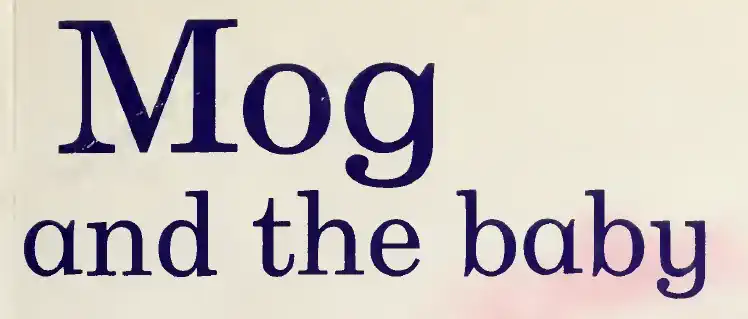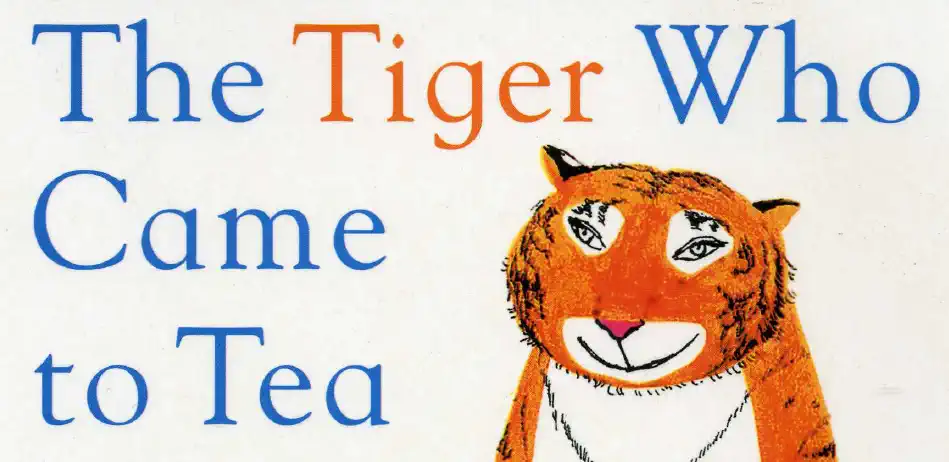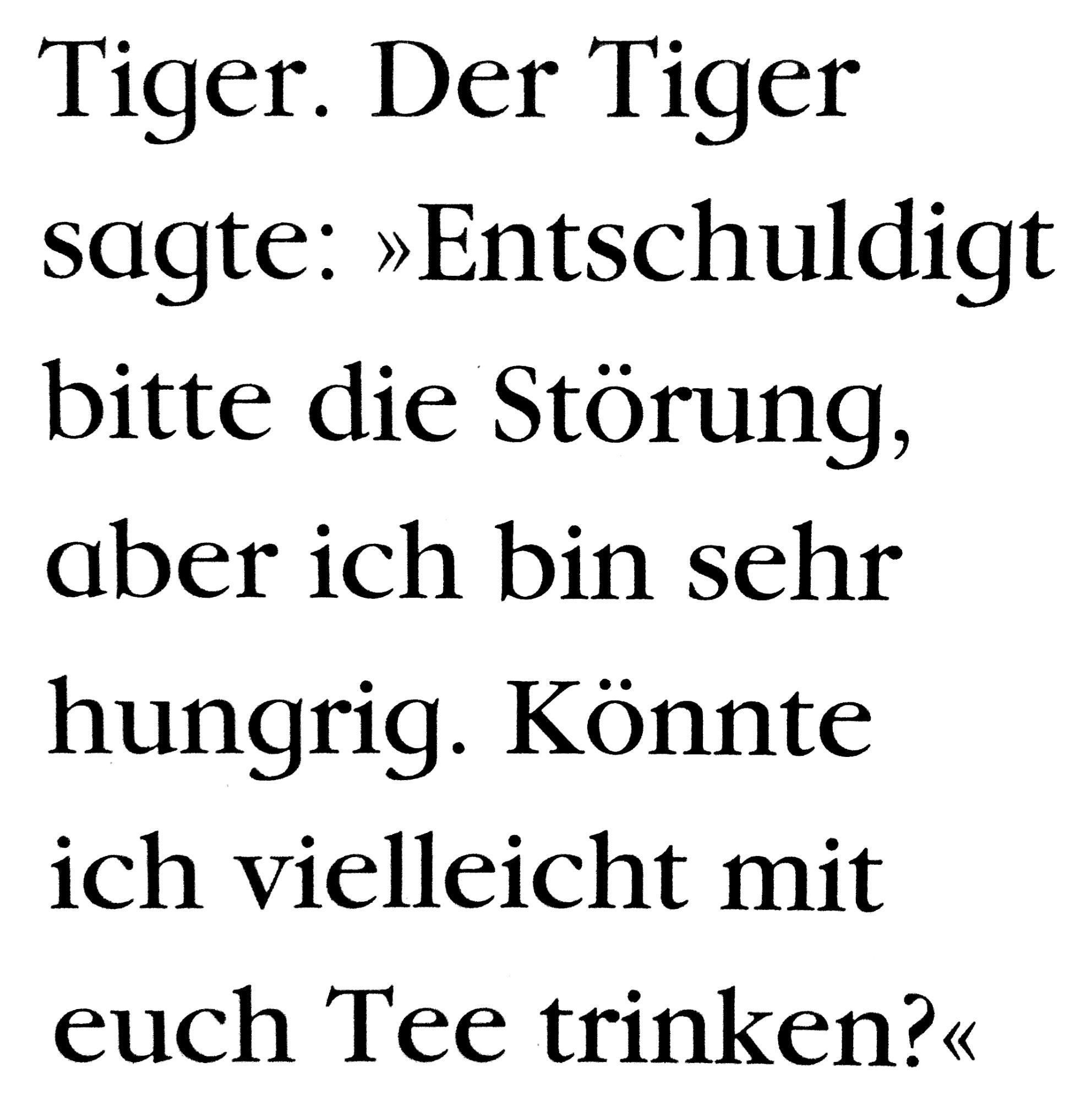
Welche Garamond-Variante ist das? (Ein Tiger kommt zum Tee)
Beim (Vor-)Lesen des Buches „Ein Tiger kommt zum Tee“ von Judith Kerr, Herausgeber Knesebeck, fiel mir eine Garamond-Variante auf, die ich leider nicht zuordnen kann.
Einige Buchstabenformen („a“ und „g“) weichen von normalen Garamond-Schnitten ab. Auch bei den alternativen Buchstabenformen von z.B. der „Adobe Garamond Pro“ bin ich nicht fündig geworden.
Die EB Garamond ist es meiner Meinung nach nicht. Da passen etliche Details nicht und vor allem sind sind die Oberlängen deutlich länger ...
Die einfachen Varianten von /g und /a werden für die Bücher der Autorin spätestens seit den späten 1980ern eingesetzt, auch in den originalen englischsprachigen Ausgaben – wahrscheinlich schon seit vordigitaler Zeit. Nicht nur bei Garalden, sondern auch bei anderen Schriftarten.
Es ist nicht unwahrscheinlich, dass der Verlag dieses Merkmal auch bei digital produzierten Neuauflagen als »Branding-Element« beibehalten will und dazu Fonts modifiziert. Gut möglich, dass das hier mit der Garamond Nova geschehen ist, die abgesehen von den schlichten Varianten exakt zu passen scheint.